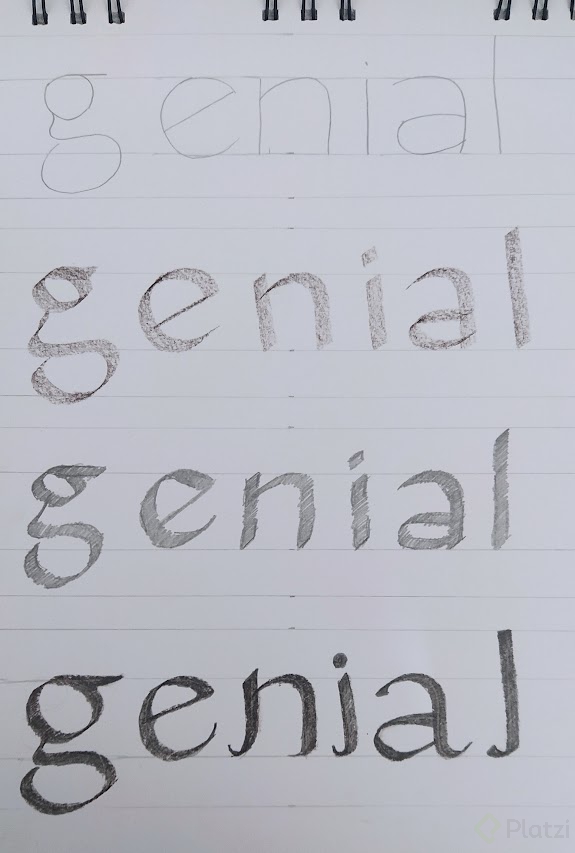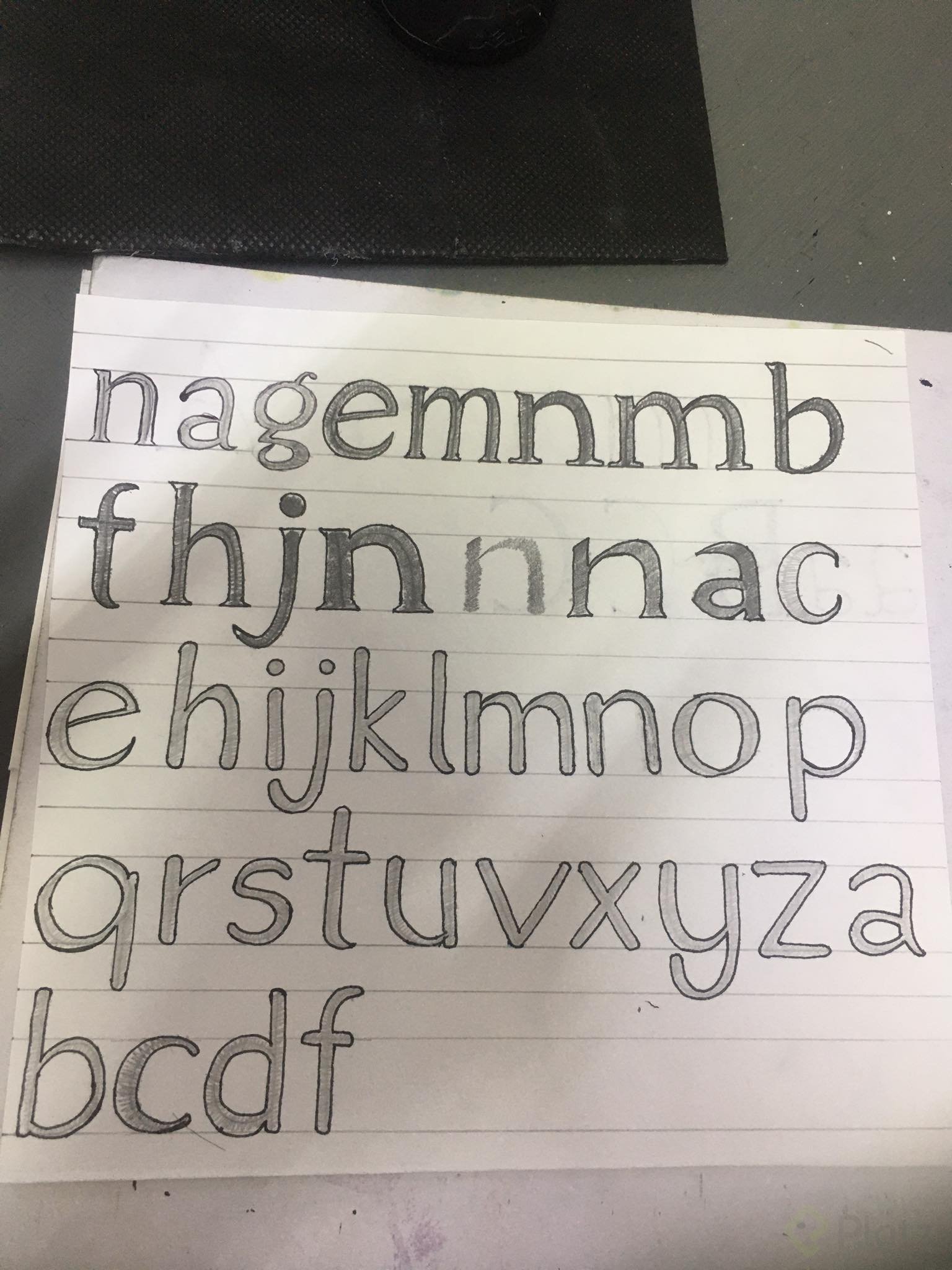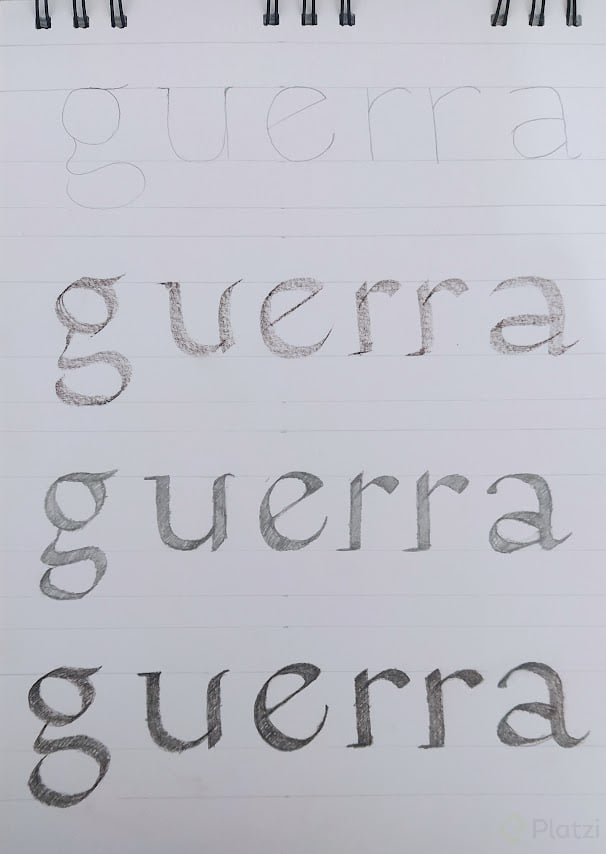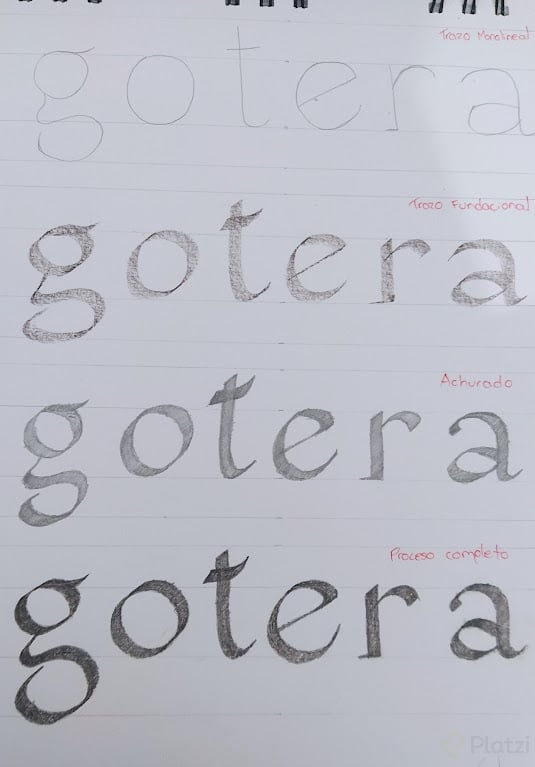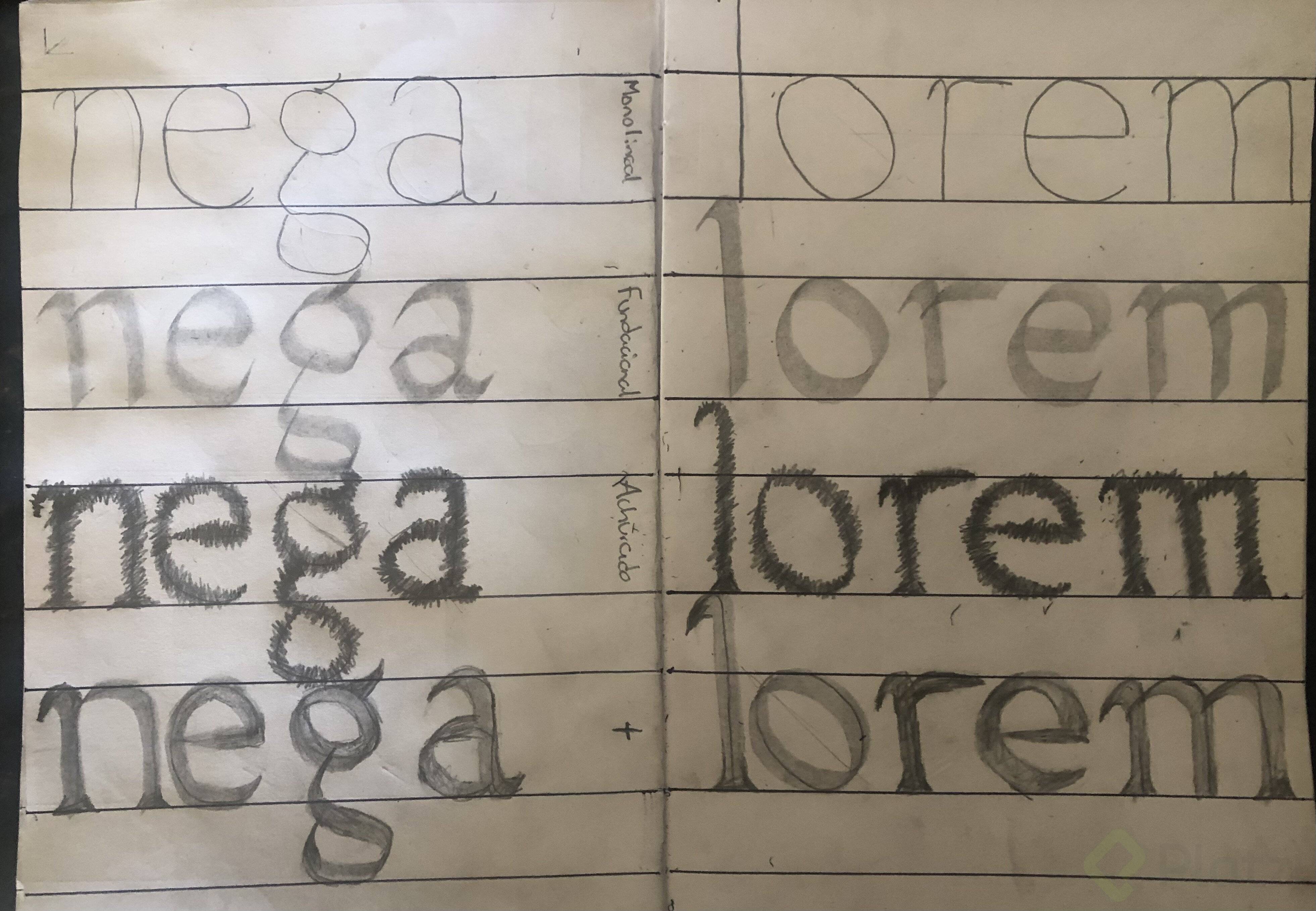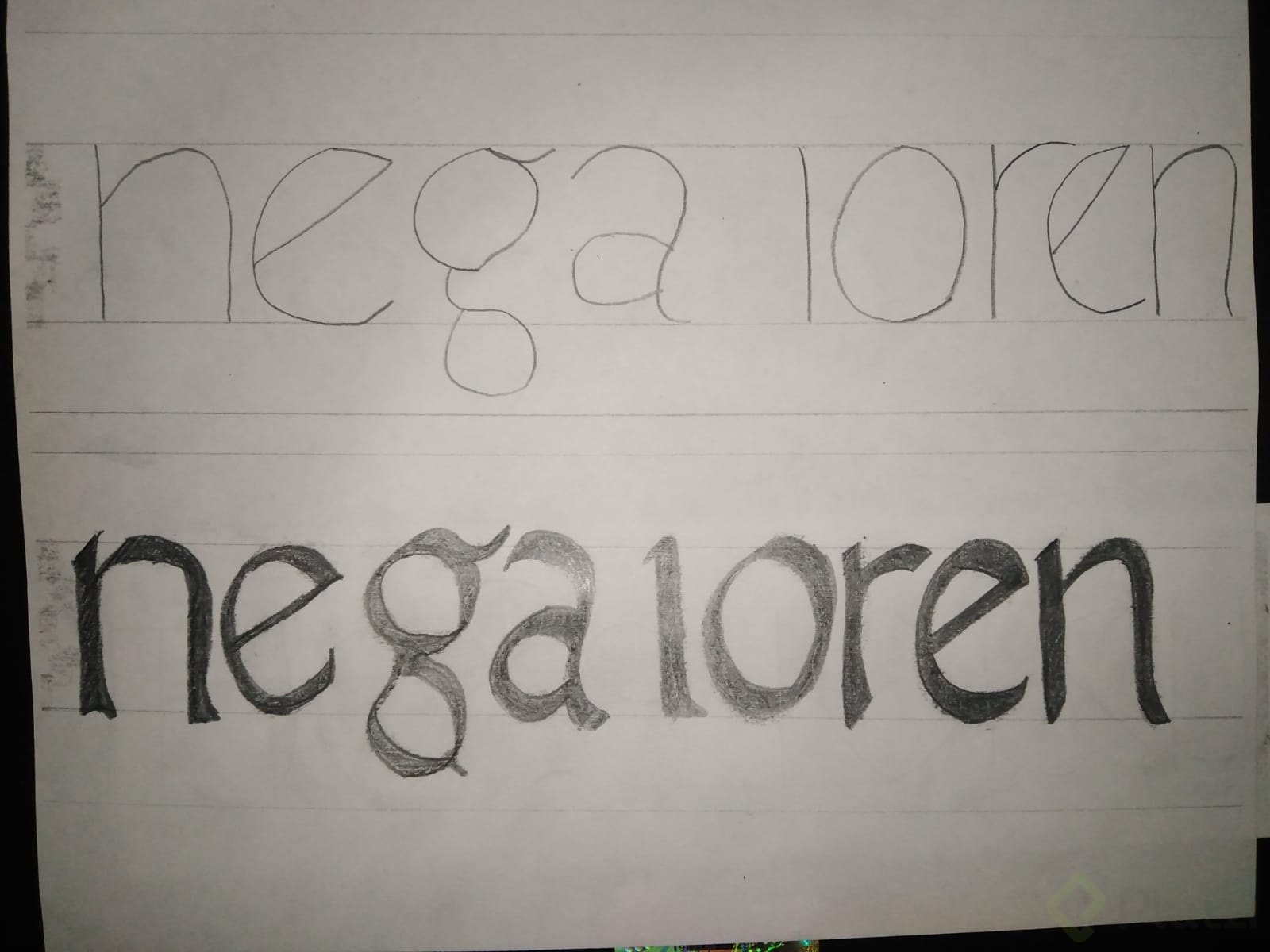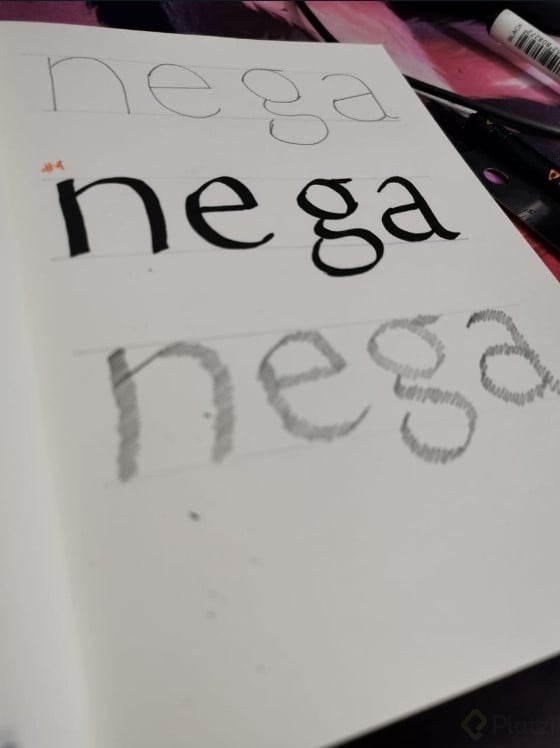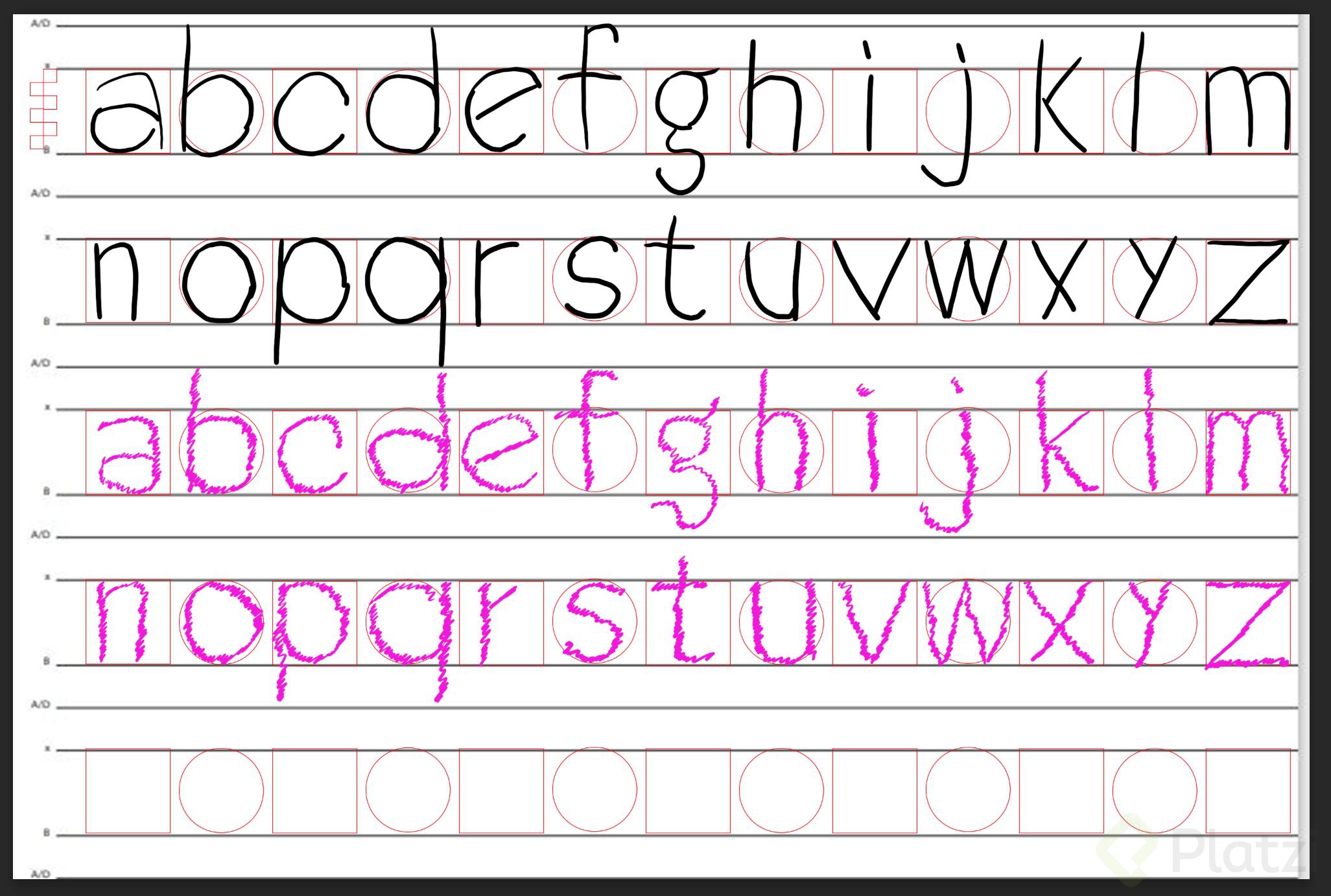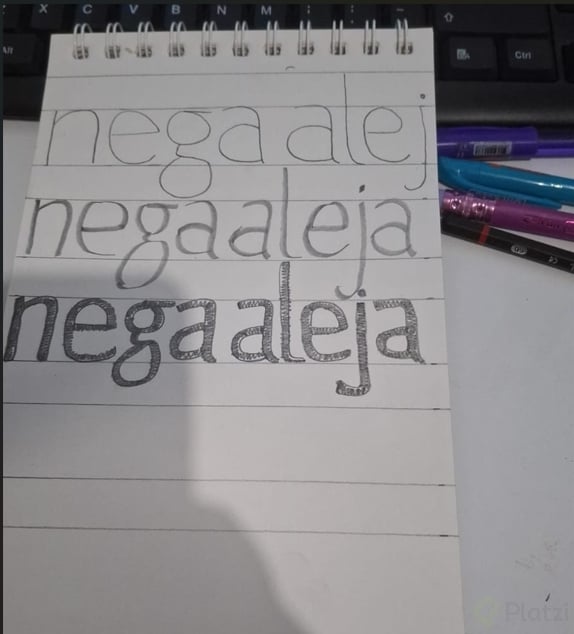
Introducción al bocetado tipográfico
El proceso de bocetado no se limita a la habilidad artística; también implica una comprensión profunda de la estructura tipográfica.
Gerrit Noordzij propone un método basado en el trazo achurado, una técnica que simplifica y organiza el diseño de letras, evitando errores comunes como el enfoque exclusivo en contornos.
1. El trazo achurado: ¿Qué es y por qué funciona?
El trazo achurado consiste en dibujar líneas en un patrón zigzagueante. Sus beneficios incluyen:
- Rapidez: captura la forma esencial de la letra sin invertir tiempo en detalles superfluos.
- Claridad: ayuda a visualizar la estructura básica sobre la que se desarrollarán los trazos más detallados.
- Flexibilidad: facilita ajustes en grosores, inclinaciones y proporciones durante el bocetado.
2. ¿Por qué evitar bocetar con contornos?
Aunque tentador, iniciar con contornos puede ser problemático:
- Falta de precisión: es difícil establecer grosores, inclinaciones y ejes con claridad.
- Desconexión caligráfica: al ignorar los principios caligráficos, se pierde cohesión y naturalidad en el diseño.
3. Caligrafía fundacional como base del bocetado
La caligrafía fundacional proporciona un enfoque sistemático para crear tipografías:
- Esqueleto: traza líneas base simples con un lápiz, estableciendo la estructura fundamental.
- Músculo: añade contraste utilizando trazos monolineales y herramientas con punta plana para controlar grosores.
- Piel: aplica el trazo achurado para detallar, ajustar ángulos y definir texturas.
4. Personalización de letras: El caso de la "G"
Cada letra tiene su carácter, y personalizarla implica:
- Esqueleto básico: define inclinación, proporción y estructura inicial.
- Inspiración visual: observa variaciones de la misma letra en diferentes tipografías.
- Detalles únicos: agrega elementos distintivos como curvas, cortes y modulaciones.
5. Métodos combinados para un diseño propio
Para garantizar que el diseño sea único y efectivo:
- Integra trazo monolineal para practicar ductus (la dirección y presión del trazo).
- Desarrolla el trazo fundacional para establecer contrastes y definir serifas.
- Usa el trazo achurado para incluir detalles finales, como texturas y ejes.
- Combina estos procesos para crear un diseño tipográfico cohesivo y original.
6. Consejos prácticos para diseñar tipografías únicas
- Experimenta con inclinaciones y proporciones: variar estas características puede dar a tus letras un carácter único.
- Juega con tridimensionalidad: agregar profundidad puede transformar un diseño sencillo en algo memorable.
- Obtén retroalimentación: aompartir tus bocetos es esencial para identificar mejoras y perfeccionar el diseño.
7. ¡Sigue practicando!
El bocetado tipográfico es un arte que combina creatividad y técnica.
Practicar con métodos sistemáticos, como el trazo achurado y la caligrafía fundacional, te permitirá desarrollar tipografías únicas y funcionales.
Con cada boceto, estarás un paso más cerca de crear mejores tipografías para tus proyectos.